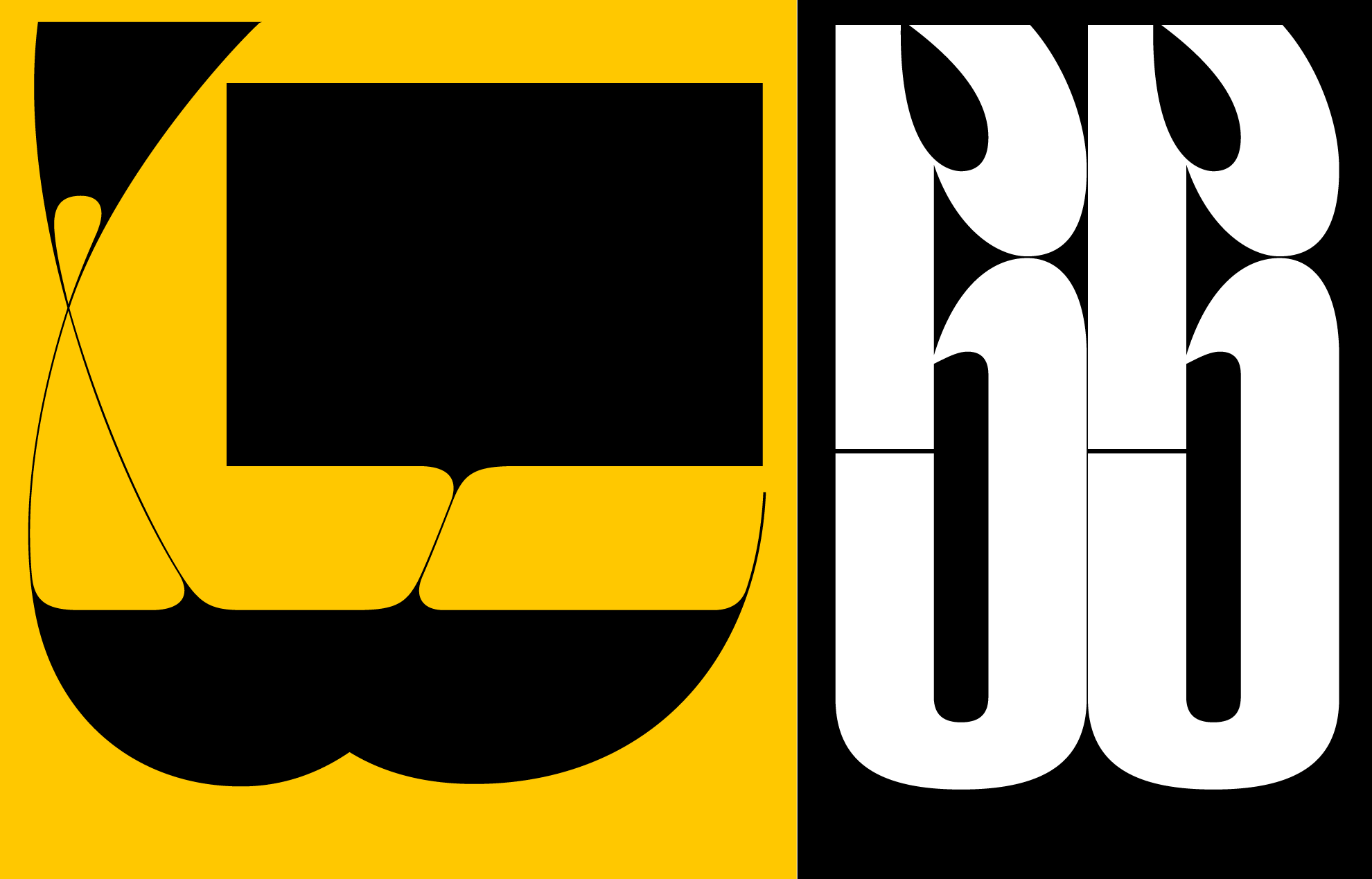
Betűkkel közösséget alkotni | Frank Fonts
Címbetű, szövegbetű, konceptuális betű és különféle típusú betűkészletek: sok magyar tervezőgrafikus készít betűt akár egyéb munkái mellett, de valahogy mégsem találunk olyan hazai kezdeményezésű gyűjtőfelületet, amely a legteljesebb módon szedné össze és tenné elérhetővé a különböző alkotásokat és a hozzá tartozó neveket. Frank Béla betűtervező erre tesz kísérletet, miközben a magyar betűtervezés hagyományának előmozdításán és elmélyítésén dolgozik.
Frank Béla a budapesti KREA Design Iskolában tanult tervezőgrafikát még 2009-ben, ennek hatására kezdett el a tipográfia iránt érdeklődni. Kezdetben csak karaktereket, szavakat tervezett, majd később első betűkészlete is megszületett. Az első pár befejezett betűterv még a fiókban vagy ingyenes fontoldalakon landolt, de hamarosan felfedezte a különféle fontforgalmazókat és foundry-kat. „Amikor az első betűcsaládomat elfogadták forgalmazásra, majd meg is vásárolta valaki, az felejthetetlen élmény volt számomra. Még így tíz év betűkkel való foglalkozás után is meghatározó a pillanat” – mondta el Béla.
A 2010-11-es időszak kezdett egyre izgalmasabbá válni számára, egyre több betűkészletet tervezett, sorra érkeztek egyedi megrendelései is mind Magyarországról, mind külföldről. 2012-2015 között a londoni Fontsmith csapatában dolgozott lokális és globális márkák számára készült arculati betűkön, majd pár év fióknak tervezés után 2018-ban aztán elindította saját, Frank Fonts névre hallgató oldalát: „Ezt megelőzően voltam tervezőgrafikus, aki mondhatni másodállásban volt betűtervező, és voltam betűtervező, aki másnak dolgozott. Ekkorra jutottam el odáig, hogy főállásban foglalkozzak a betűtervezéssel, saját, egyszemélyes stúdiómban” – tette hozzá. „Jelenleg mindent egymagam intézek, ami elég sok feladat, de minden vonatkozását élvezem. Tervezek, ügyfelekkel kommunikálok és igyekszem a szerintem legjobb licenszszerződést ajánlani nekik, a saját szolgáltatásaim mellett. A Frank Fonts az egyik legjobb lehetőség arra, hogy szakmailag és emberileg is fejleszthessem magam” – folytatta.
A kínálat jelenleg három betűcsaládra korlátozódik. Az elsőként felkerült betűkészlet a nyolc különböző változatban elérhető és nem mellesleg a 2019-es Type Directors Club betütervezési, azaz a szakma egyik legrangosabb nemzetközi díjával büszkélkedő Kraken Slab, amely szögletes talpának (slab serif) és egyedi karakterének, részleteinek köszönhetően válik karakteressé, és kiválóan használható címbetűként. A Kraken Slab felfedezhető többek között Máthé Dórának a Közlekedési Múzeum pályázati munkáit bemutató kiállításhoz készített tervein vagy a de_form stúdiónak a Mai Manó Házban megrendezett, Erik Kessels művészetét bemutató tárlathoz készített kreatívjain.
A Frank Fonts kínálatában megtalálható továbbá a Rupp Mono úgynevezett monospace betűtípus (olyan betűkészlet, amelynek karakterei vízszintesen egyforma szélességű helyet foglalnak el – a szerk.), amely hosszabb folyószövegek megjelenítésére használatos, valamint a legfrissebb, dekoratív jellegű Blokk névre hallgató betűcsalád, amely Budapest különböző korszakainak tipográfiai örökségéből inspirálódik.
„Bár a kínálat még aránylag szűk, ezen belül is igyekszem jól kiegyensúlyozottan reprezentálni a betűtervezési stílusokat. A következő fél évben érkezik pár hosszabb szöveghez is jobban használható sans betűcsalád, amelyek bétaverzióját igyekszem minél több designer segítségével tesztelni. A jövőbeli felhasználóktól érkező, minél nagyobb számú visszajelzés a tervezési folyamat során felbecsülhetetlen érték. Bizonyos értelemben együtt tervezzük a betűket” – emelte ki Béla.
Frank Béla nem csak saját betűkészleteinek népszerűsítésén dolgozik; nemrég debütált a magyar betűtervezésnek és tervezőknek dedikált Hungarian Type Design névre hallgató Instagram-oldala is.  „Nem tipográfiáról vagy kalligráfiáról lesz szó, hanem szigorúan véve a betűtervezésről. Ennek itthon nincs olyan gazdag hagyománya, mint például a lengyeleknél vagy a cseheknél, nem is beszélve az angol, német vagy holland betűtervezésről, de ennek ellenére is bőven van anyag. Egy ideje igyekszem ezzel kapcsolatban információkat, képanyagot gyűjteni, de elég korán eszembe jutott, hogy ez mást is érdekelhet, így igyekeztem megtalálni a módját annak, hogy a legkönnyebben tegyem elérhetővé azokat. Így a Hungarian Type Design jelenleg egy Instagram-oldal formájában jött létre, de a közeljövőben hamarosan elindul egy hozzá tartozó weboldal is” részletezte a tervező.
Hogy miért? Szerintem szükség van egy olyan felületre, ami hazai és külföldi érdeklődők számára nyújt jó rálátást a magyar betűtervezésre, az itthoni és külföldön élő magyar alkotókra. Ahol lehet tájékozódni, tanulni és közösséget alkotni a betűk körül, azok ürügyén” – folytatta.
A felületen bemutatott első alkotó, Reiner Imre elismert magyar művész és betűtervező, de egyre több olyan kortárs és múltbéli alkotóra kerül majd sor, akik betűket alkottak és alkotnak.